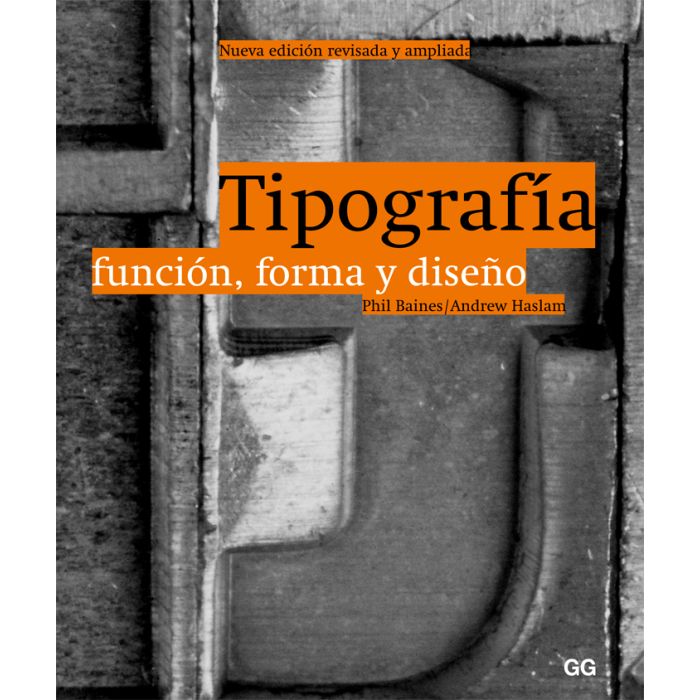
Tipografía. Función, forma y diseño
Un libro de Phil Baines, Andrew Haslam
Tipografía. Función, forma y diseño proporciona unos conocimientos básicos esenciales a los lectores de cualquier nivel, desde estudiantes hasta profesionales. La tipografía es la notación y organización mecánica del lenguaje que se usa para hacer múltiples copias, ya sea por medios impresos o electrónicos. Su historia en Occidente comienza en 1455, con la publicación de la Biblia de Gutenberg, llamada 'de cuarenta y dos líneas', aunque la historia de la escritura y los alfabetos se remonte a miles de años atrás. El libro, cuidadosamente estructurado y profusamente ilustrado, introduce al lector en todos los aspectos clave del tema, desde la historia del lenguaje y la escritura, hasta el invento de los tipos movibles y la evolución de los sistemas digitales actuales. Ofrece una visión de conjunto de la asombrosa variedad de tipos de letra existente y constituye una guía práctica para el uso del tipo como elemento significativo del diseño en todos los medios.
Índice de contenidos: I Definición Introducción ¿Qué es la tipografía? II Función Tipografía y lenguaje Lenguaje: el sistema hablado Otras opiniones Lenguaje: el sistema escrito Gramática Léxico Teorías de la comunicación III Forma Hacia un alfabeto de 26 letras Hacia las letras de caja alta y de caja baja El desarrollo de las letras Clasificar y describir tipos Fuentes y modelos IV Elaboración y diseño La tipografía no es rotulación Grabado de punzones manual y tipos de metal movibles Fundición y composición mecánica de tipos de metal movibles Fotocomposición Más allá de lo físico: la composición tipográfica digital V Estructura Planteamientos del diseño Diseñar con tipo en dos dimensiones Estructurar un diseño: las retículas La tipografía en el tiempo: el cine y los nuevos medios VI Convenios La estilística del detalle en un texto ... Combinaciones de teclado en Macintosh para el juego de caracteres ISO Latino 1 (teclados británico y americano) Combinaciones de teclado en Windows 95/98 para el juego de caracteres ISO Latino 1 (teclados británico y americano) Glosario Cuadro cronológico de diseñadores de tipo, parte 1: 1400-1900 Cuadro cronológico de diseñadores de tipo, parte 2: desde 1900 hasta hoy Bibliografía comentada Quiénes son los diseñadores en este libro Formatos de papel ISO Índice Créditos de las ilustraciones Agradecimientos Dedicatoria |
Texto del primer capítulo: ' I Definición Introducción Desde la llegada de los ordenadores personales, la autoedición y, más recientemente, el desarrollo de internet, millones de personas se han ido habituando a usar fuentes y a trabajar con tipos. Sin embargo, a quienquiera que preguntemos qué es la tipografía, le va a resultar difícil definir cuáles son sus límites o posibilidades. La tipografía se ocupa de estructurar y organizar el lenguaje visual. El diseño de tipos se ocupa de la creación de las unidades que deben organizarse, los caracteres que constituyen un tipo. El diseño de la forma del tipo y la tipografía están encaminados a transmitir un mensaje. Este último aspecto coloca firmemente a la tipografía en la base de una disciplina más amplia, la del diseño gráfico. La cuestión de cómo usar la tipografía para transmitir un mensaje puede subdividirse en dos. La primera parte se ocupa del aspecto o estilo de la tipografía. Éste varía según la época y el lugar, o el diseñador y el cliente; así, en ocasiones, la tipografía juega un papel secundario o hasta invisible, mientras que en otras, su papel es dominante, reflejando la inspiración del diseñador y llegando incluso, a veces, a reclamar su condición de 'arte'. En este libro mostraremos y debatiremos algunos de esos planteamientos. La segunda parte se refiere a los aspectos prácticos del trabajo tipográfico, como legibilidad, escala y formato, que constituyen la preocupación dominante de esta obra. El libro está concebido en parte para proporcionar buenos consejos a los estudiantes y en parte como una fuente de información concisa, capaz de trascender a la época estudiantil del lector. Inevitablemente, todo libro es un reflejo de los prejuicios de su autor, y el que ahora nos ocupa también refleja nuestra manera de enseñar. Uno de nuestros objetivos es que su ámbito sea amplio, de manera que en un solo volumen se reúna una información que actualmente está dispersa en muchos libros. Aspiramos a proporcionar consejo práctico de una manera abierta, no dogmática. Quizá, lo único que pedimos al lector es que lea nuestro libro, pase a conocer otros escritos sobre la materia y, después, saque sus propias conclusiones. Le advertimos de que este libro también incluye mucha información 'objetiva', y no tiene porqué necesitarla toda a la vez. Hemos subdividido el libro en capítulos específicos que pueden ser leídos y comprendidos de forma independiente y a medida que vaya siendo preciso. En muchos lugares, se ha optado por separar el detalle del texto principal, presentándolo a la manera de 'episodios laterales' que pueden ser leídos independientemente. ¿Qué es la tipografía? Para empezar, es importante señalar que ciertos términos han tenido significados ligeramente diferentes a lo largo de los distintos períodos de la historia. En los tiempos digitales que estamos viviendo, los términos 'fuente' y 'tipo' se usan indistintamente, pero en la época del tipo de metal fundido sus significados eran bastante diferentes. A lo largo de este libro hemos tratado de usar las palabras con sus significados originales precisos. Así, tipo es el objeto físico, un bloque paralelepipédico de metal (aleación tipográfica) que tiene en su cara superior, en relieve e invertida, la imagen de una letra o signo para la impresión por sistema tipográfico. Fuente es un conjunto o surtido completo de letras, signos y blancos tipográficos de una clase o tipo determinados, en un tamaño o estilo concretos. Se llama 'carácter' a un signo de cualquier sistema de escritura; y, de forma más precisa, a un cierto estilo o forma particular de escritura, a mano o de imprenta. Desde finales del siglo XIX, el término se aplica a un conjunto de estilos afines: letras 'cursiva', 'redonda', 'negrilla', 'cursiva negrilla', 'versalita', etcétera. Una vez establecido que la tipografía se ocupa tanto de la creación de caracteres como de su composición para transmitir un mensaje, nos dimos cuenta de que era preciso proponer una definición más clara, en la que se sugiriese, por ejemplo, en qué se diferenciaba el tipo de la escritura o de la rotulación. A este fin, lo más lógico parecía empezar por acudir al diccionario, pero cuál sería nuestra sorpresa ante las definiciones de tipografía que en él se proponían, a saber: 1 Arte, oficio, o proceso de componer tipo e imprimir con él. 2 Planificación, selección y composición de tipo para una obra impresa. (traducido directamente de Collins concise dictionary, 1999). Esta definición refleja con tanta intensidad la naturaleza de oficio tradicional de la palabra y su relación con la industria de la imprenta de la que nació, que muy bien podía haber sido redactada hace cien años. Pero hoy en día se nos antoja manifiestamente inadecuada y, aun sin ser del todo falsa, resulta demasiado limitada. Entonces, se nos ocurrió la idea de proponer un debate sobre definiciones potenciales de la disciplina entre pequeños grupos de estudiantes de diseño gráfico y tipografía. Sus ideas inciden y aclaran diferentes aspectos del tema: 'La arquitectura de las ideas y la elaboración del lenguaje', una definición que revela el papel de la tipografía en la construcción de la narración, creando espacios intelectuales a través de los que el lector puede desplazarse. 'El modelado de la experiencia', una definición que incide en la idea de que la forma del mensaje influye en la interpretación del contenido por parte del lector. 'El manejo de las letras' pone el énfasis en la capacidad organizadora del tipógrafo y alude a la creación de una estructura. 'El motor del aprendizaje' incide en la idea de que la tipografía permite y facilita la lectura y la escritura. 'Una prolongación formal de la memoria' subraya el papel de la tipografía en la documentación y conservación de ideas, lo que permite la reflexión. 'Pintar con palabras' considera la tipografía como un arte expresivo en el que el contenido emocional de las ideas se refleja en la manipulación de la forma de las palabras. Semejante diversidad de definiciones no es sino un reflejo de la complejidad de la tipografía y del alcance de su influencia, al tiempo que constituye una prueba fehaciente de su constante necesidad de adaptación, tanto a las nuevas tecnologías como a la visión que del futuro puedan tener sus usuarios. Por último, el periplo intelectual en la búsqueda de una definición tiene bastante más valor que el propio punto de llegada, o que la ciega repetición de las creencias de una generación anterior. Qué duda cabe que es importante familiarizarse con las definiciones del pasado, pero siempre que no nos quedemos atrapados por sus dogmas. Todas las definiciones nos proporcionan un punto de partida potencial para desarrollar nuestra obra profunda e investigadora. Así pues, no hay una definición establecida de la disciplina, sino que cada una de ellas deberá ser redefinida y adaptada constantemente en relación a la práctica. Sin embargo, nos ha parecido que podría ser útil formular nuestra propia definición con el fin de estimular ulteriores debates en torno a los parámetros y límites de la disciplina. Tipografía: Notación (x) y organización mecánica (y) del lenguaje (z). (y) Mecánica En alusión a la ciencia de las máquinas, la automatización -sea física o digital- precisa de una tarea, abriéndose paso hacia un objetivo definido a través de un proceso estructurado. La idea de lo mecánico sugiere una de las diferencias primordiales entre tipografía y rotulación: la tipografía se refiere a escribir usando unidades repetibles, mientras que la rotulación es única. Esta idea de manufactura se comenta en el Capítulo IV. (x) Notación Sistema de símbolos convencionales que se adopta para documentar una disciplina a través de un código gráfico. El código empleado en este libro es el alfabeto occidental o latino, cuya evolución se explica en el Capítulo III. (z) Lenguaje Abarca los códigos oral y escrito: conjunto de sonidos articulados que en sus diversas combinaciones forman palabras que se corresponden tácitamente con objetos e ideas; organización de palabras que señala significados complejos a grupos familiarizados con el código. El lenguaje es el tema del próximo capítulo. En esta definición nos hemos esforzado en alejarnos de los datos específicos de la imprenta y en reafirmar la función de la tipografía, a saber: documentar, conservar y repetir el conocimiento basado en la palabra y ubicarlo firmemente en el núcleo central del diseño de la comunicación moderno. El debate acerca de la enseñanza del diseño tipográfico se ha centrado, tradicionalmente, en la apariencia de la tipografía en relación con el mensaje. Se ha tendido a analizar principalmente la estética y las consideraciones técnicas, como selección de fuentes, jerarquías, organización espacial, retículas y estilo. Sin ánimo de negar la pertinencia de esas cuestiones en todo lo que hacemos como diseñadores, tal vez pasen por alto lo más obvio: que la tipografía es intrínsecamente lenguaje visual. En el seno del sistema de enseñanza, no deja de ser una extraña anomalía el hecho de que un tema -el lenguaje- y el sistema de notación ideado para registrarlo -la tipografía- se enseñen en instituciones inconexas. En las universidades se enseña antropología, lingüística, desarrollo del lenguaje, idiomas y literatura, mientras que la tipografía se enseña en las escuelas de arte y diseño. Y sin embargo, la tipografía es al lenguaje lo que los mapas son a la geografía, las partituras a la música y el álgebra a las matemáticas. ¿Es posible que un tema y su sistema de documentación afín no se investiguen conjuntamente? Desde nuestro punto de vista, es de vital importancia que los tipógrafos empiecen a comprender los rasgos del lenguaje al mismo tiempo que aprenden los convenios para su notación y los procesos técnicos para su reproducción. Nos guste o no, en el medio urbano estamos completamente rodeados por el lenguaje, a través del tipo. Sus mensajes han penetrado hasta tal punto en nuestras mentes, que nos resulta prácticamente imposible imaginar un mundo sin tipo, un mundo sin libros o bibliotecas, revistas o mapas, señales de circulación, televisión o anuncios. Como la rueda, la electricidad y el motor de combustión interna, la tipografía sostiene la vida occidental moderna. Desde el momento mismo en que nos despertamos, lo primero que vemos al abrir los ojos ya está invadido por el tipo: el despertador, el dial de la radio, las marcas del champú, la pasta de dientes, el café o los cereales del desayuno; estamos siendo bombardeados por mensajes tipográficos que demandan nuestra atención. ÁY todo ello antes incluso de haber podido echar la primera ojeada al periódico! Hoy día, el tipo va emparejado a una multiplicidad de mensajes exhibidos en la gama de formatos más variada. Johannes Gutenberg, quien, por cierto, murió en la pobreza, difícilmente habría podido imaginar las profundas ramificaciones que iba a tener su invento de rotulación modular, el tipo.' |